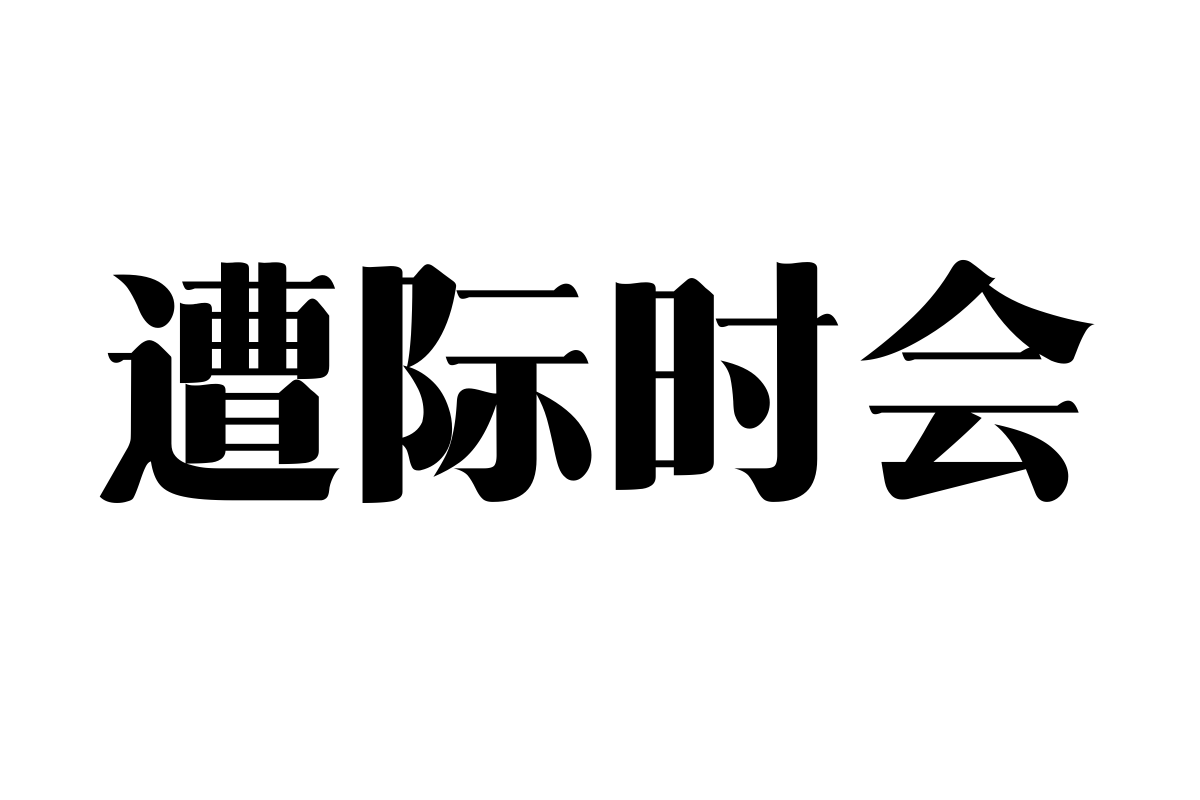
三极清宋简体-粗是一种特殊的字体,它结合了现代和传统的元素。这种字体的特点是:
1. 简洁明了:三极清宋简体-粗的字形简单,线条流畅,易于阅读。
2. 现代感:这种字体的设计灵感来源于现代设计,线条干净利落,没有多余的装饰。
3. 传统感:虽然简洁,但仍然保留了一些传统的元素,如笔画的粗细变化和一些基本的笔画结构。
4. 可读性高:由于其简洁明了的设计,这种字体在各种场景下都非常实用,无论是打印还是屏幕显示。
总的来说,三极清宋简体-粗是一种既现代又传统的字体,适合用于需要清晰、易读的文本。